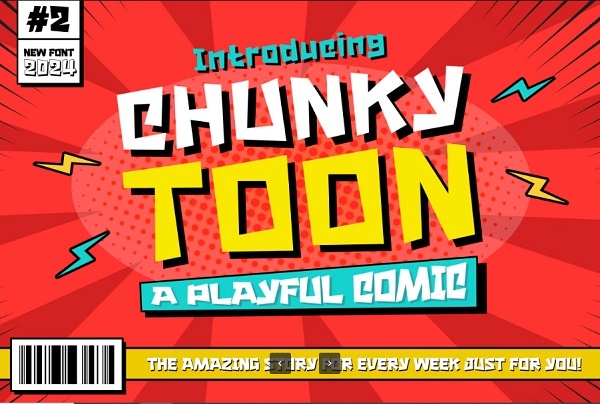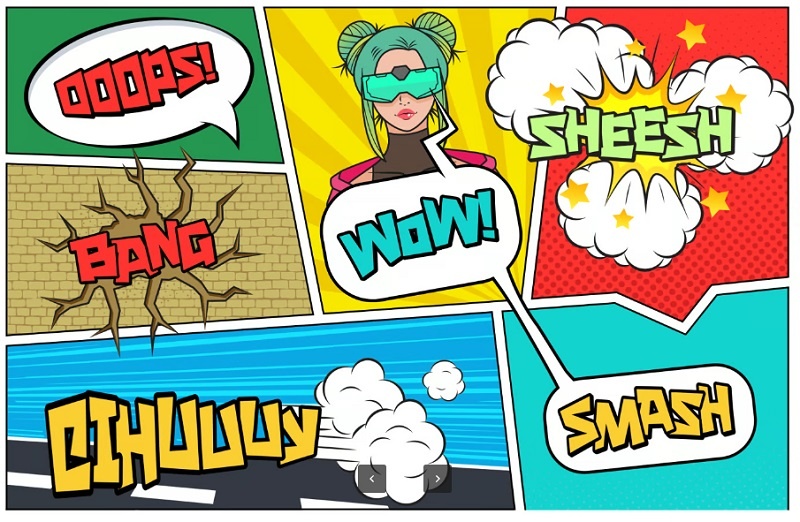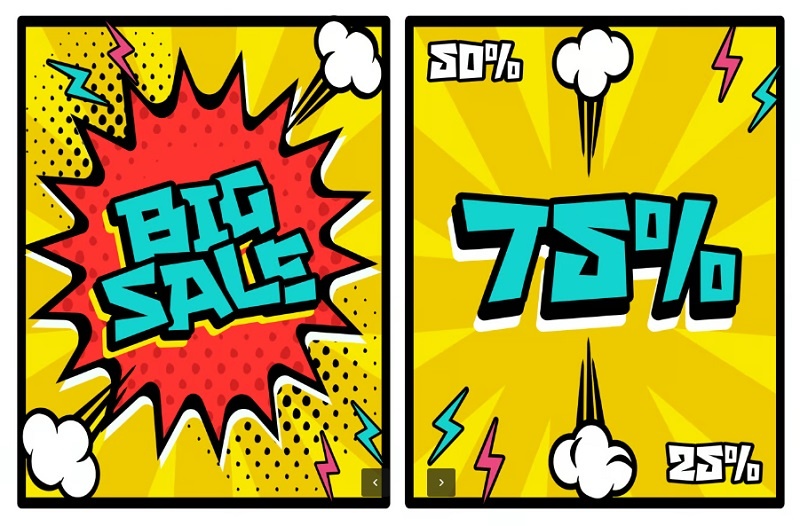
فونت جذاب انگلیسی چانکی تون Chunky Toon
فونت جذاب انگلیسی چانکی تون
فونت جذاب انگلیسی چانکی تون Chunky Toon. این فونت جذاب با تم شاد و کارتونی برای پروژه‌هایی مانند پوسترهای کودکانه، لوگوهای بازی و اپلیکیشن‌های کودکانه، کارت‌های دعوت، کمیک‌ها، یا تبلیغات و سرگرمی عالی است. فونت‌های کارتونی انگلیسی با طراحی شاد و رنگارنگ خود، حس شادی و نشاط را به بیننده منتقل می‌کنند.